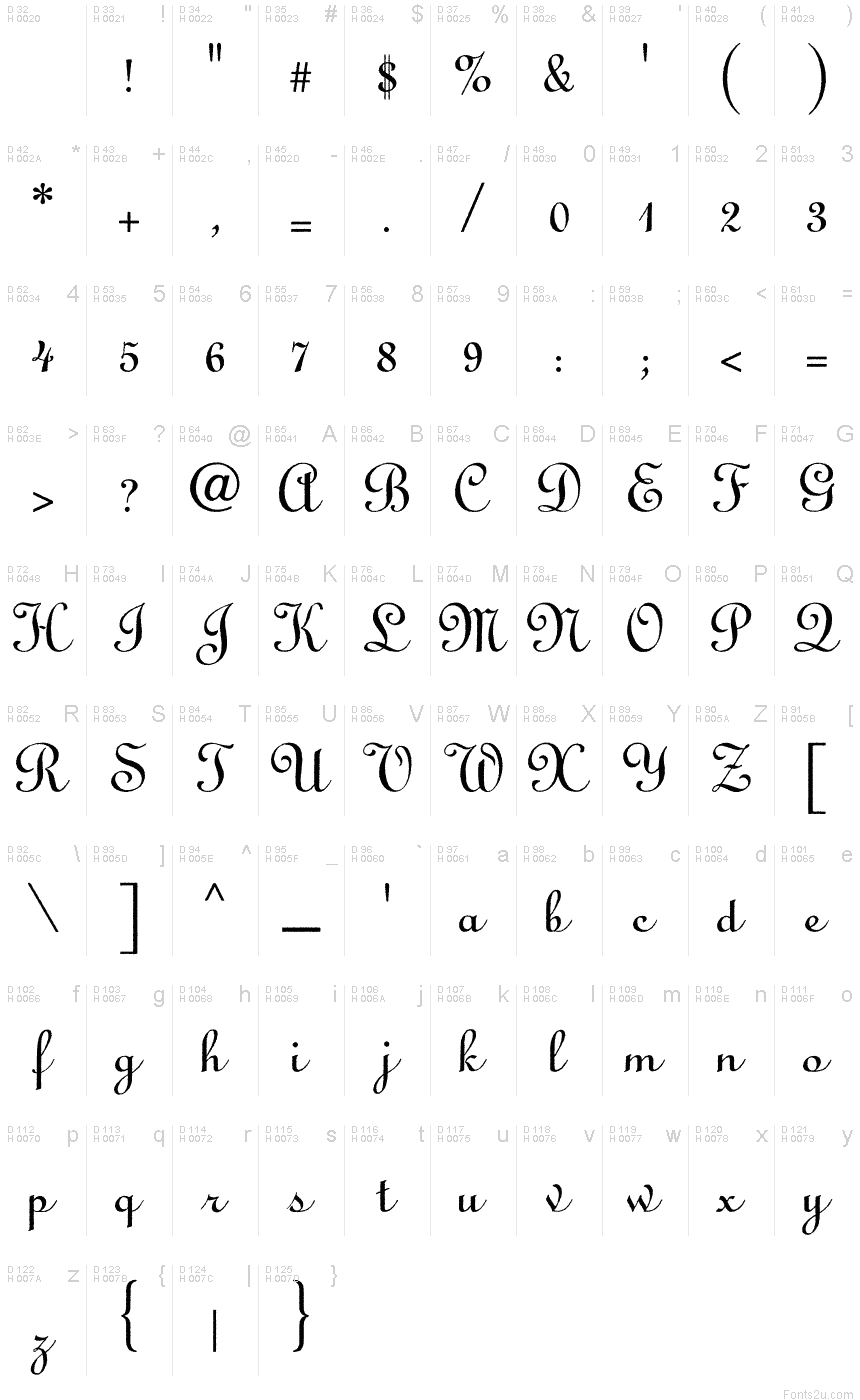
Annabel Antique Script
Annabel Antique Script autorstwa Jose Alberto Reyes Galveza to darmowy, formalny krój pisma o charakterze kaligraficznym z zamaszystymi pętlami i silnym kontrastem kresek. Jego połączone litery płynnie płyną, a lekko nieregularne krawędzie sprawiają, że pismo nie wygląda na nadmiernie dopracowane.
Projektanci pracujący nad projektami ślubnymi i gastronomicznymi uznają go za odpowiedni na zaproszenia, menu i butikowe opakowania, gdzie obfite zawijasy przywodzą na myśl tradycyjne pisarstwo ręczne. W branży wydawniczej może nadać okładkom wspomnień lub tytułom romansów historycznych klimat odręcznego napisu.